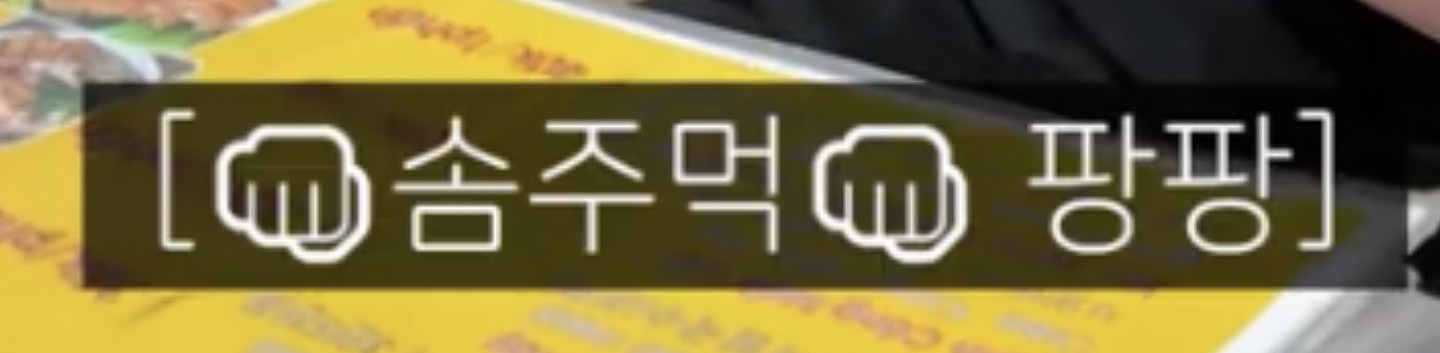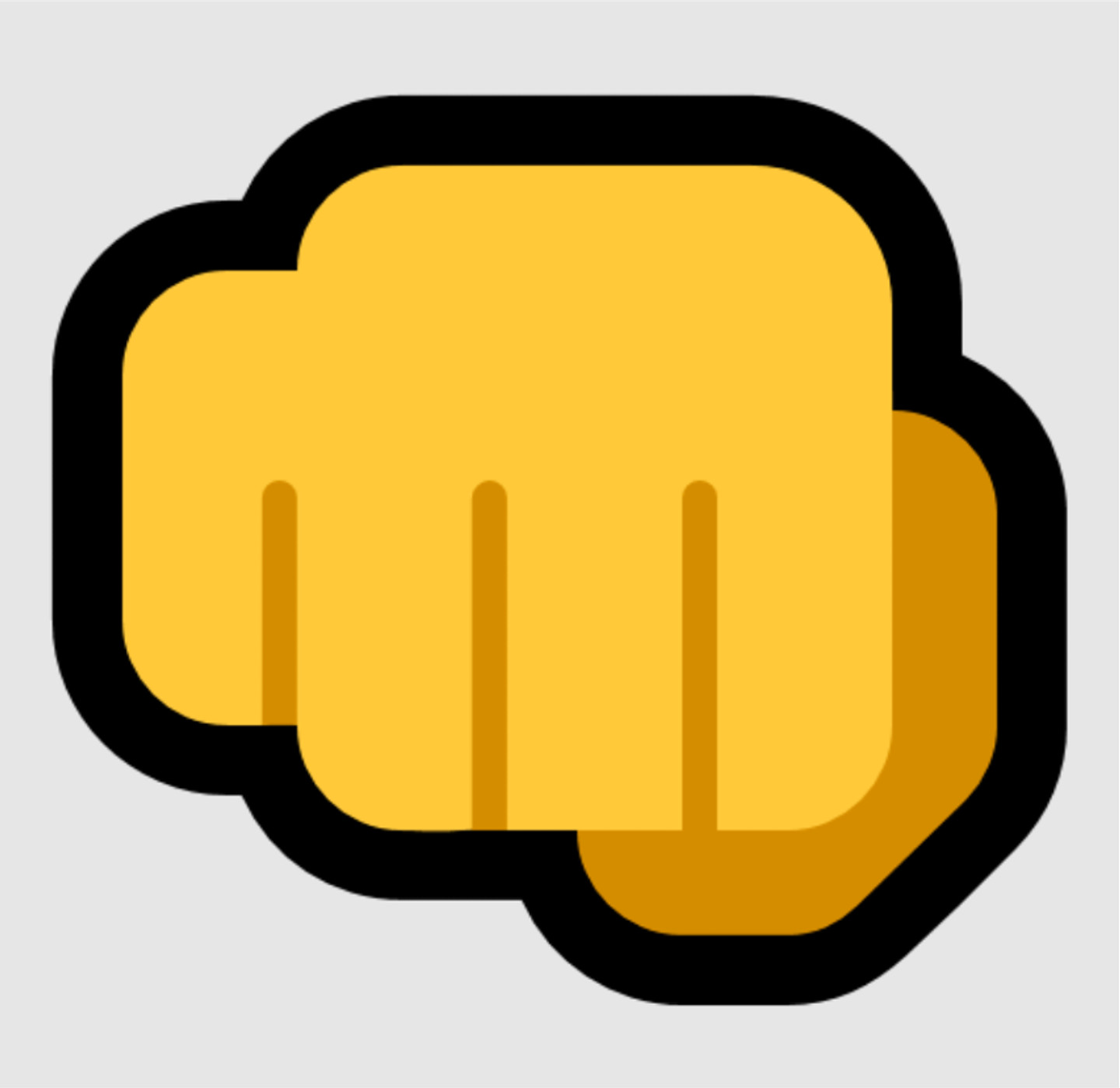
저렇게 이모지가 아웃라인?테두리만 있게 하는건 어떻게 하는걸까요? 저 폰트(나눔스퀘어)로 해봐도 안 나오던데.. 혹시 따로 복붙해서 써야하는거려나요? 전지적할부지시점(뿌빠티비)에서도 저거 많이 쓰던데 너무너무 알고싶어요 ㅠㅠ + 제가 맥을 쓰는데 맥에서는 나눔스퀘어로 적용해도 바뀌진 않네요 ㅠㅠ
Segoe UI Emoji
해당 폰트의 아웃라인 버전으로 보입니다. (윈도우 10 한정)